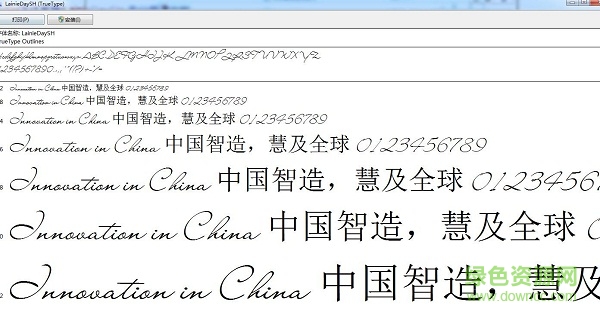
lainiedaysh.ttf常規(guī)字體是一款華麗的英文花體字體,線條飛揚(yáng)灑脫,有一種舞動(dòng)的美感,表現(xiàn)力非常強(qiáng),適合用在廣告設(shè)計(jì)、影視、包裝設(shè)計(jì)等領(lǐng)域,歡迎大家在綠色資源網(wǎng)免費(fèi)下載!